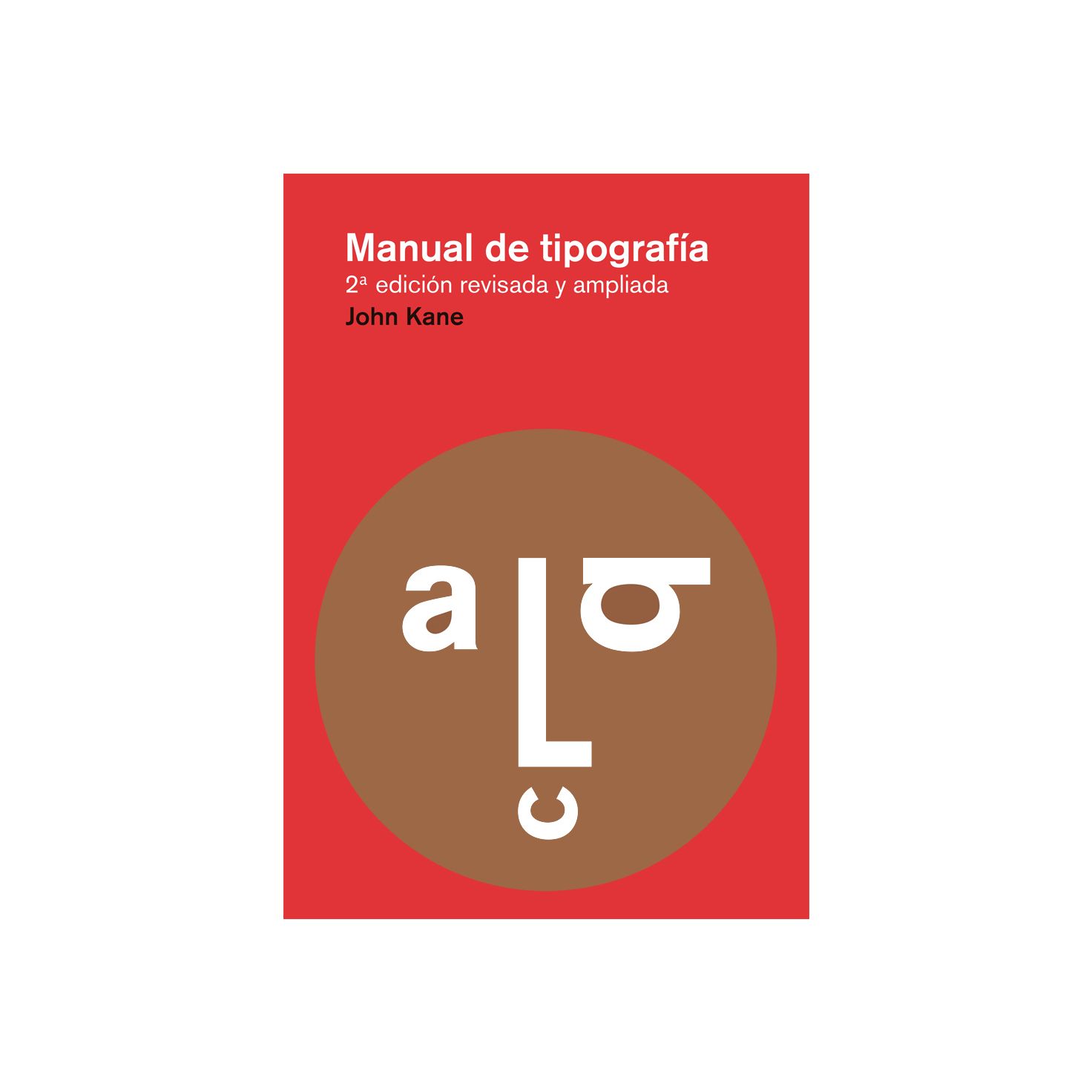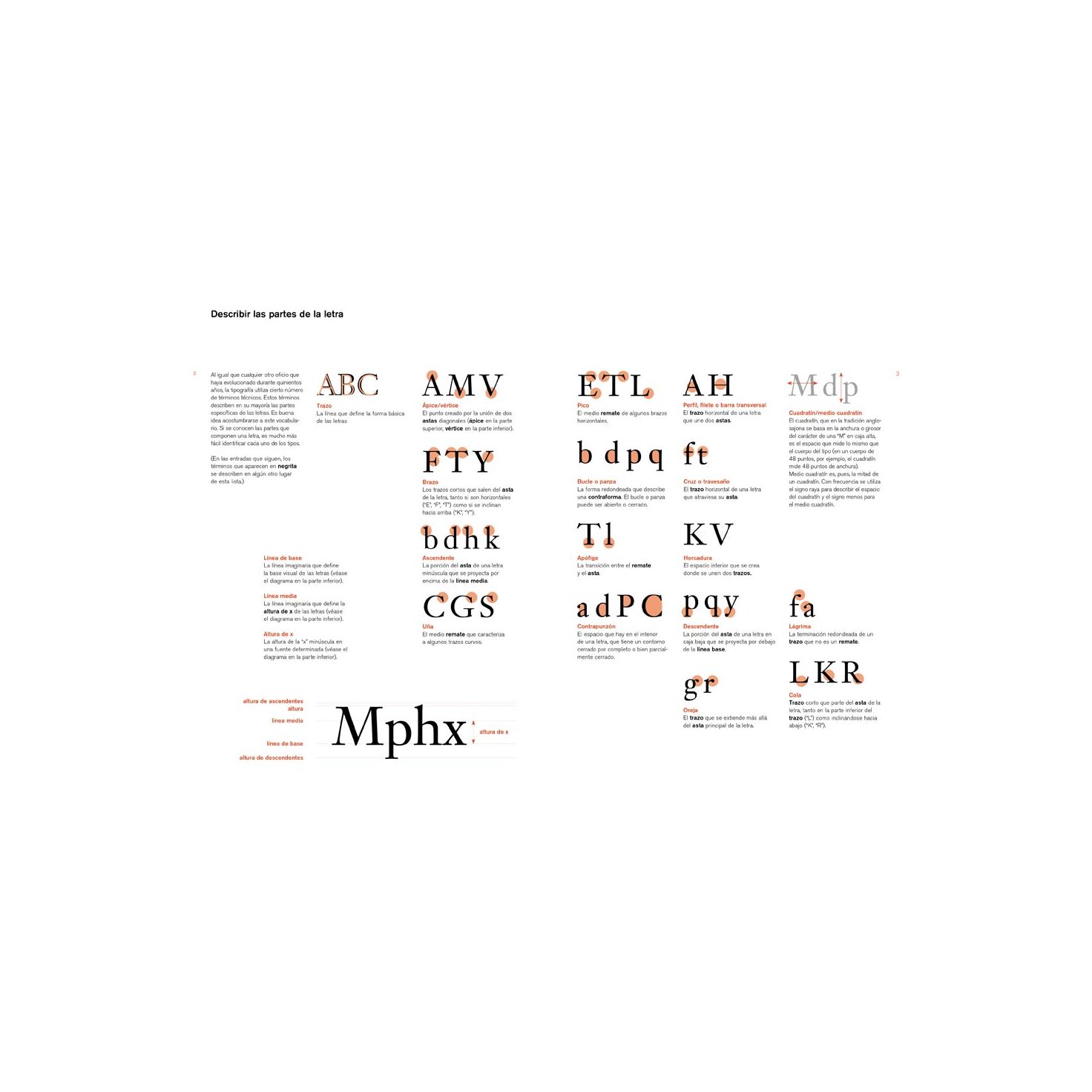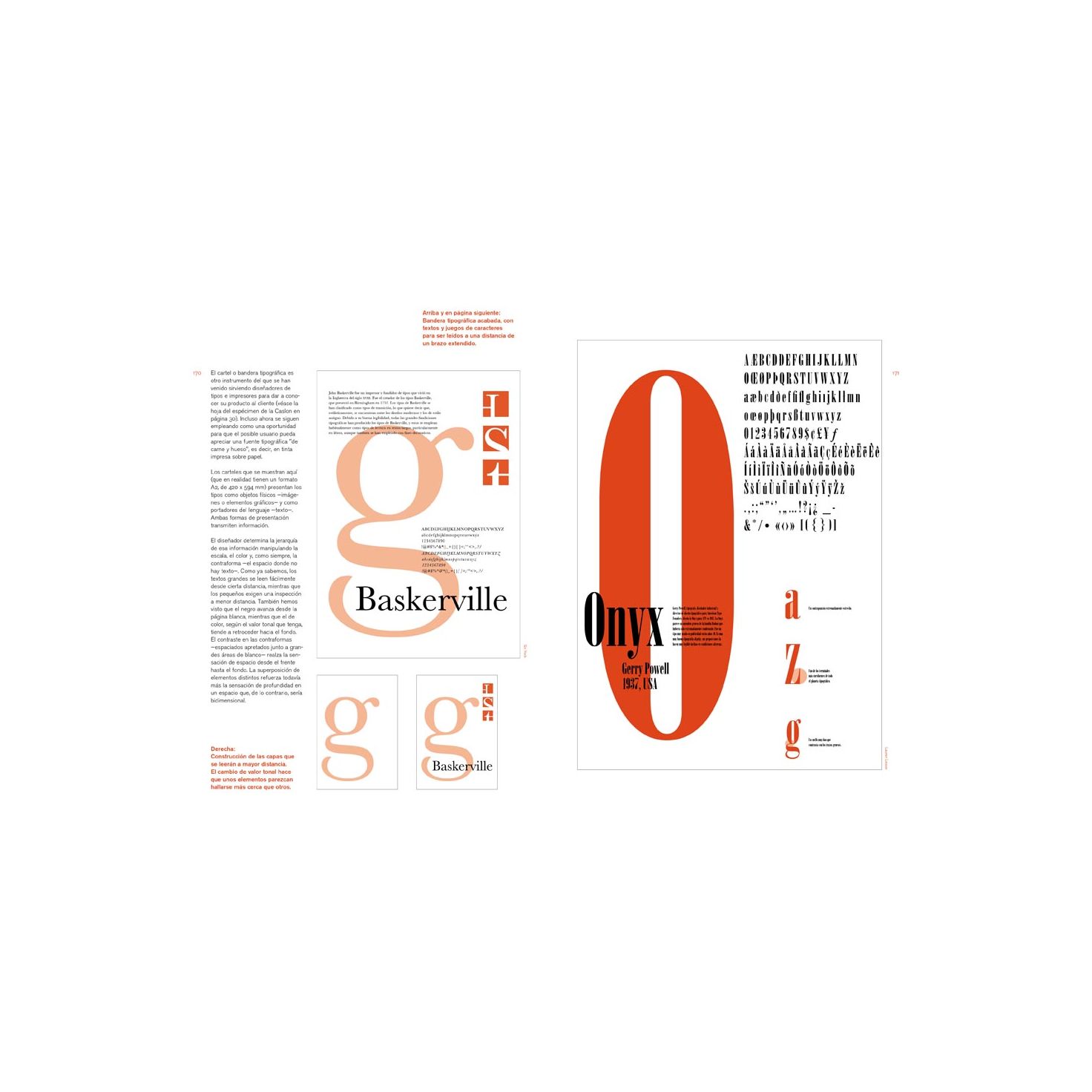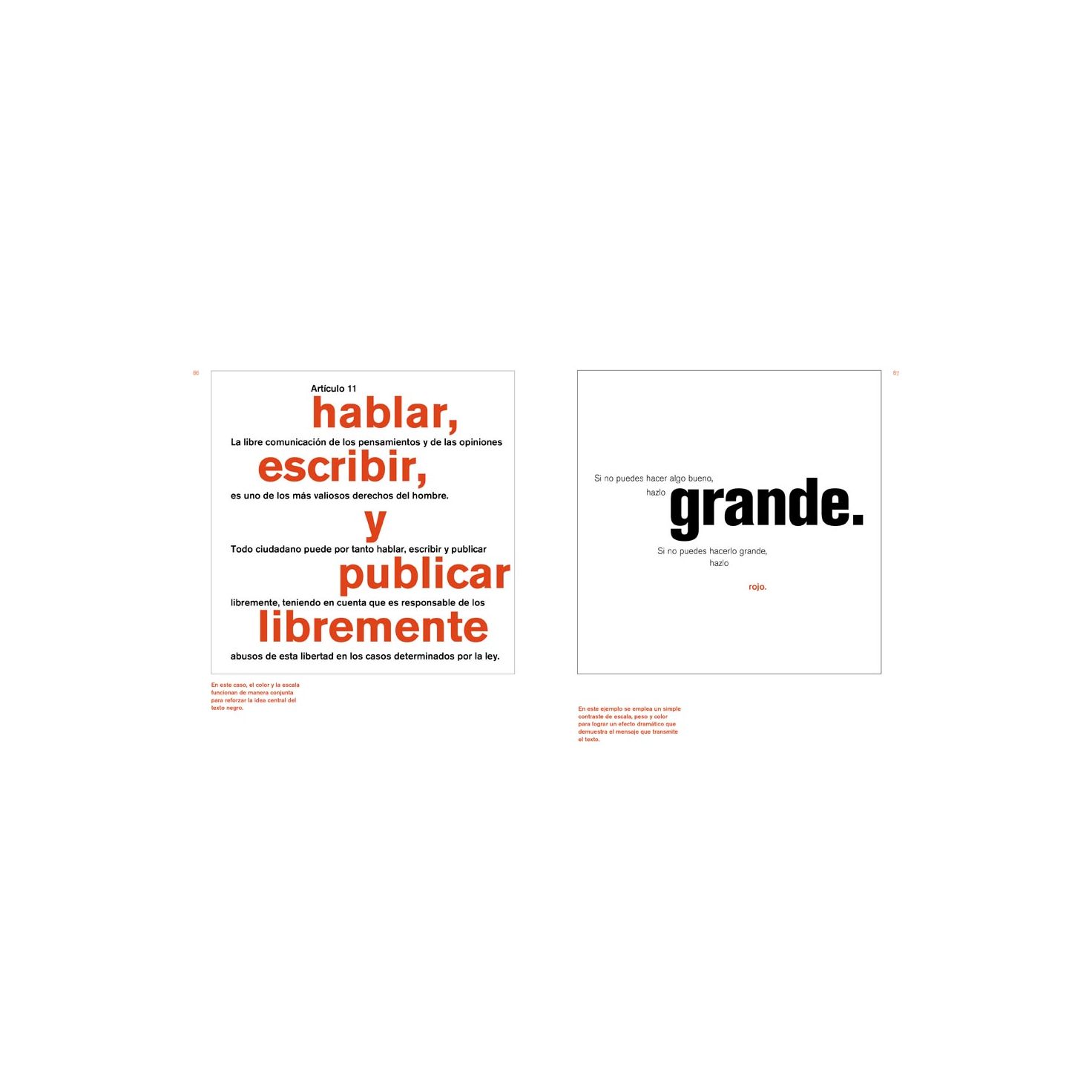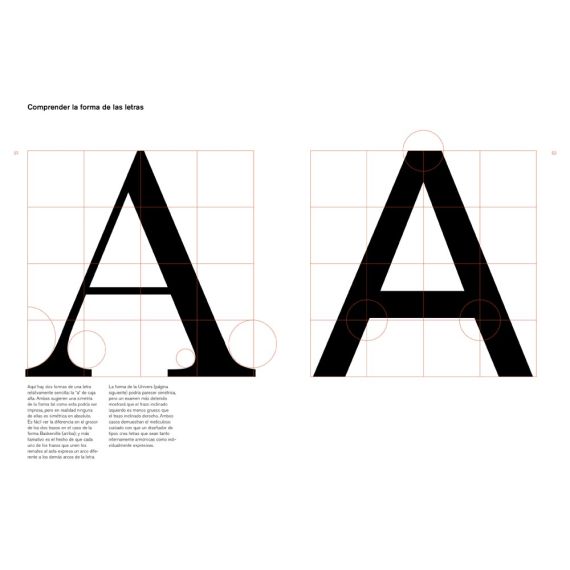
Manual de Tipografía de John Kane (segunda edición revisada y ampliada)
AccederEste Manual de tipografía es una introducción a todo lo que cualquier estudiante o profesional del diseño gráfico debe saber sobre tipografía para desarrollar una sensibilidad y unos conocimientos tipográficos bien fundamentados.
El libro expone los principios básicos de la tipografía y principales aplicaciones mediante una equilibrada combinación de historia, teoría y práctica. Así, el lector encontrará en estas páginas desde la descripción de las partes de la letra o la clasificación de los diferentes tipos, a la explicación de cómo se compone el texto en la página o cómo funcionan los sistemas de retículas. Pero también encontrará una breve y reveladora historia de la tipografía así como numerosos ejemplos y ejercicios prácticos que pretenden ayudar a adquirir un conocimiento experiencial de la disciplina.
Extracto de la presentación
Diseñar es resolver problemas.
El diseño gráfico consiste en resolver problemas creando signos. La tipografía es un conjunto de signos especialmente rico, porque consigue hacer visible el lenguaje. Saber trabajar con la tipografía es esencial para crear un diseño gráfico eficaz.
Dicho esto, puedo afirmar que este es un libro práctico.
A lo largo de los últimos veinte años que he dedicado a enseñar tipografía, he sido incapaz de encontrar un solo texto que les explicase con claridad a los estudiantes principiantes la compleja conjunción de mensaje, imagen e historia que conforma la tipografía. Algunos de los mejores textos sobre historia carecen de ejemplos suficientes; algunos de los mejores textos teóricos se dirigen más a los profesionales que a los novatos.
Y no hay ningún texto que ofrezca a los estudiantes la información fundamental de contexto de forma relacionada con los ejercicios básicos que se realizan en cualquier curso introductorio. Lo que pretendo con este libro es presentar los principios básicos y las aplicaciones tipográficas de un modo que refleje lo que ocurre en el aula, y corroborar esa información con una serie de ejercicios que consoliden los conocimientos adquiridos.
Mi intención es acompañarte a ti, estudiante principiante de diseño gráfico, hasta el punto en el que puedas comprender y demostrar los principios básicos de la tipografía. Si el instinto es la suma del conocimiento y la experiencia, este libro constituye un intento de ampliar ambas cosas con el fin de reforzar tus propias intuiciones tipográficas.
También debería señalar que este es un libro para autodidactas. Lo que yo sé sobre tipografía lo aprendí mediante la lectura, práctica y observación. Tuve la suerte de leer a Emil Ruder en primer lugar. Y también la de poder trabajar en Boston en una época en la que había docenas de profesionales de gran talento que estaban intentando resolver los mismos problemas a los que yo me enfrentaba cotidianamente, a medida que todos íbamos pasando desde los tipos de plomo hacia los tipos digitales de nuestros Macs, pasando por la fase intermedia de la fotocomposición. Lo que aprendí de todo este proceso fue la aplicación constante de la teoría en la práctica, a sentir un gran respeto hacia las letras y una búsqueda incesante de esos momentos en los que lo personal se unía —o por lo menos se acercaba— a lo platónico.
Paul Rand escribió en una ocasión: “La tipografía es un arte. La buena tipografía es Arte”. Y aquí radica el problema tanto de los profesores como de los alumnos. El oficio puede enseñarse. El arte está dentro de cada persona. Para muchos estudiantes que empiezan el hecho de que en tipografía no haya reglas seguras, ni exista un camino infalible para llegar al éxito, resulta frustrante. La dificultad pedagógica reside en que la tipografía es un sistema de principios basado en la experiencia, y esos principios siguen evolucionando a medida que evolucionan el lenguaje y los medios de comunicación. En innumerables ocasiones los estudiantes han preguntado: “¿Esto es correcto?”, cuando de hecho no existe “lo correcto” en tipografía.
La cuestión que deberían plantearse es: “¿Esto funciona? ¿Es útil?”. Los diseñadores utilizan la tipografía como respuesta; como respuesta a un mensaje, a un público, a un medio. La única forma de saber si un tipo funciona bien es a través de una observación directa e informada. Hace falta tiempo, y hacen falta ensayos y errores para saber qué es lo que funciona, y para no preocuparse por lo que pueda ser “correcto” o no.
Acceder«El libro es muy completo, revisando la anatomía de la letra, su evolución histórica, su uso y su cuidado en diseño editorial. [...] La edición es francamente bonita -para ser una rústica-, impreso todo ello a dos tintas: negro y Pantone 032. Me encantan estos detalles.» (Pedro Arilla, Don Serifa, 04/12/2012)